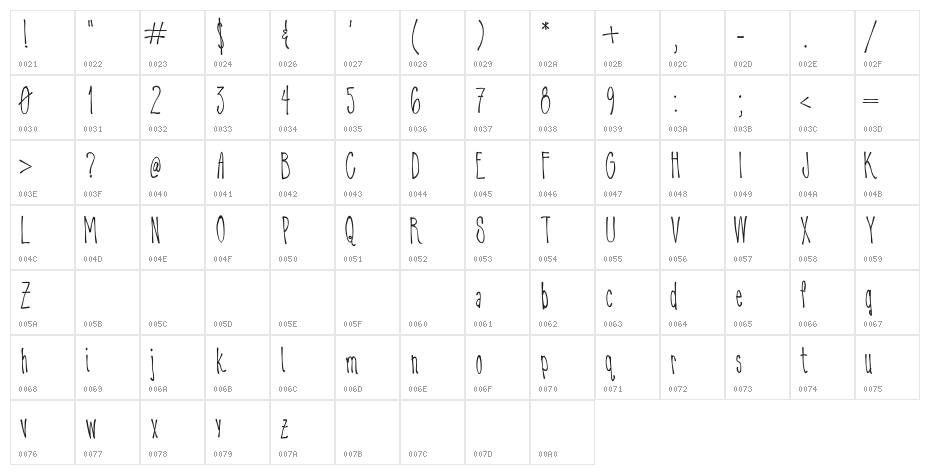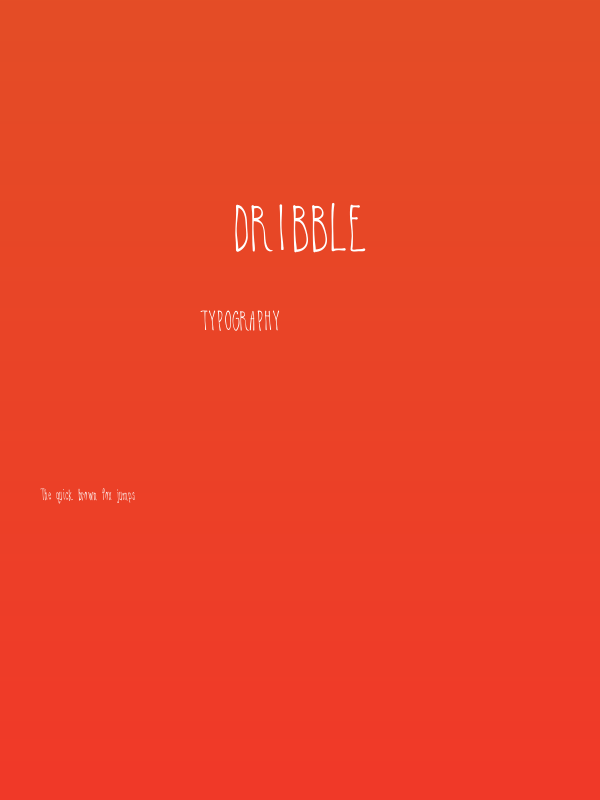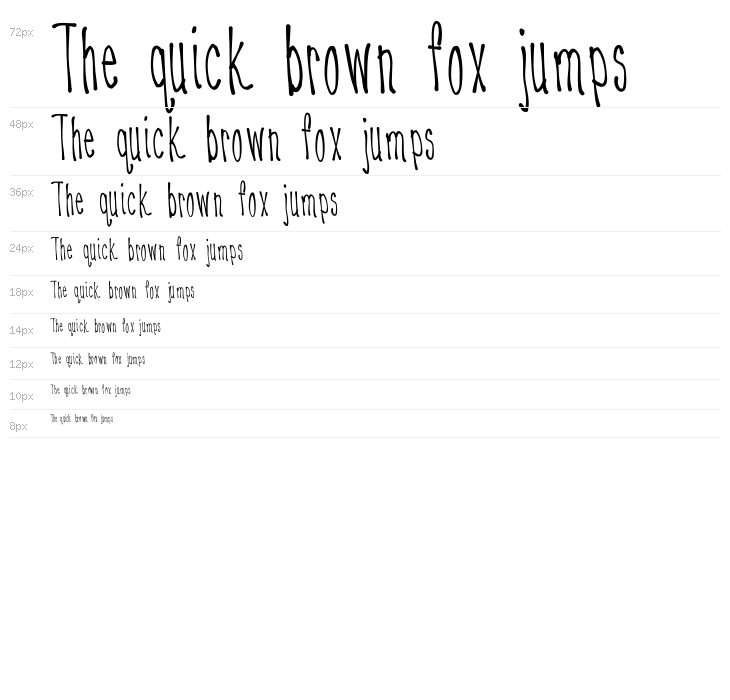
Dribble Font
| Область применения | Headlines, Artistic projects, Branding |
| Рекомендуемые проекты | Ideal for children's books, creative posters, greeting cards, and artistic branding projects. |